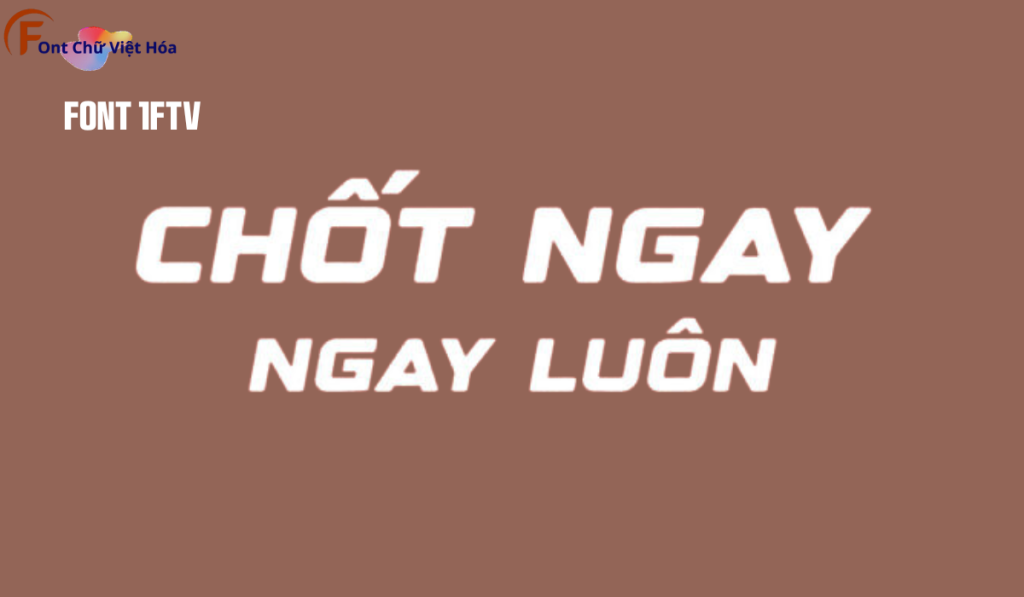
Font 1FTV Designer Việt hóa
Tác giả: 1FTV Designer
Bộ Font: 1FTV
Phân loại: Cá tính, độc đáo
Font 1FTV Designer là một font chữ đặc biệt nằm trong bộ 1FTV, mang phong cách sans-serif không chân hiện đại và sáng tạo. Với các đường nét rõ ràng và góc cạnh tinh tế, font này mang lại cảm giác phá cách và phù hợp với các thiết kế đồ họa đòi hỏi tính độc đáo cao như logo, poster, hoặc branding. 1FTV Designer cung cấp nhiều tùy chọn về kích thước và độ dày, giúp dễ dàng tạo ra các tiêu đề nổi bật hoặc nội dung thu hút sự chú ý. Font này đã được Việt hóa, hỗ trợ tốt cho các nhà thiết kế Việt Nam khi thực hiện các dự án sáng tạo.